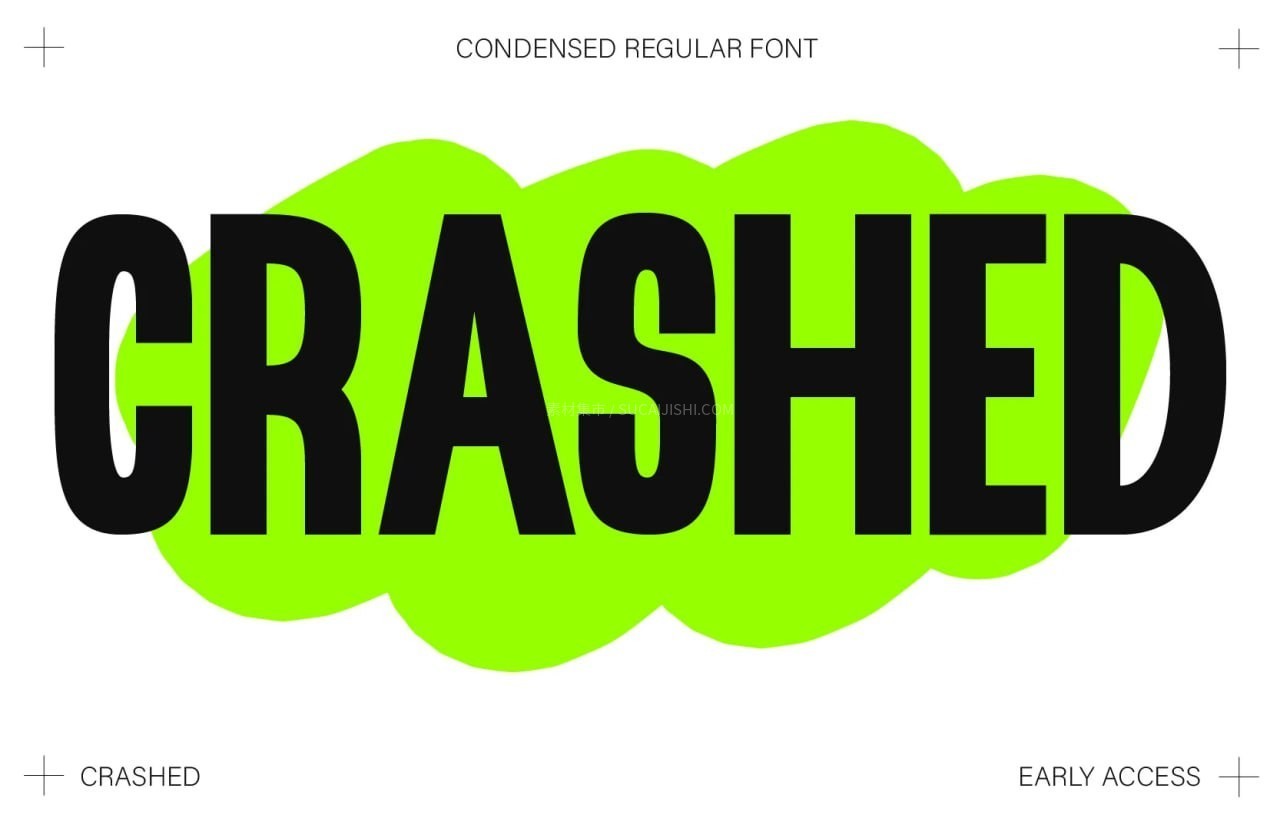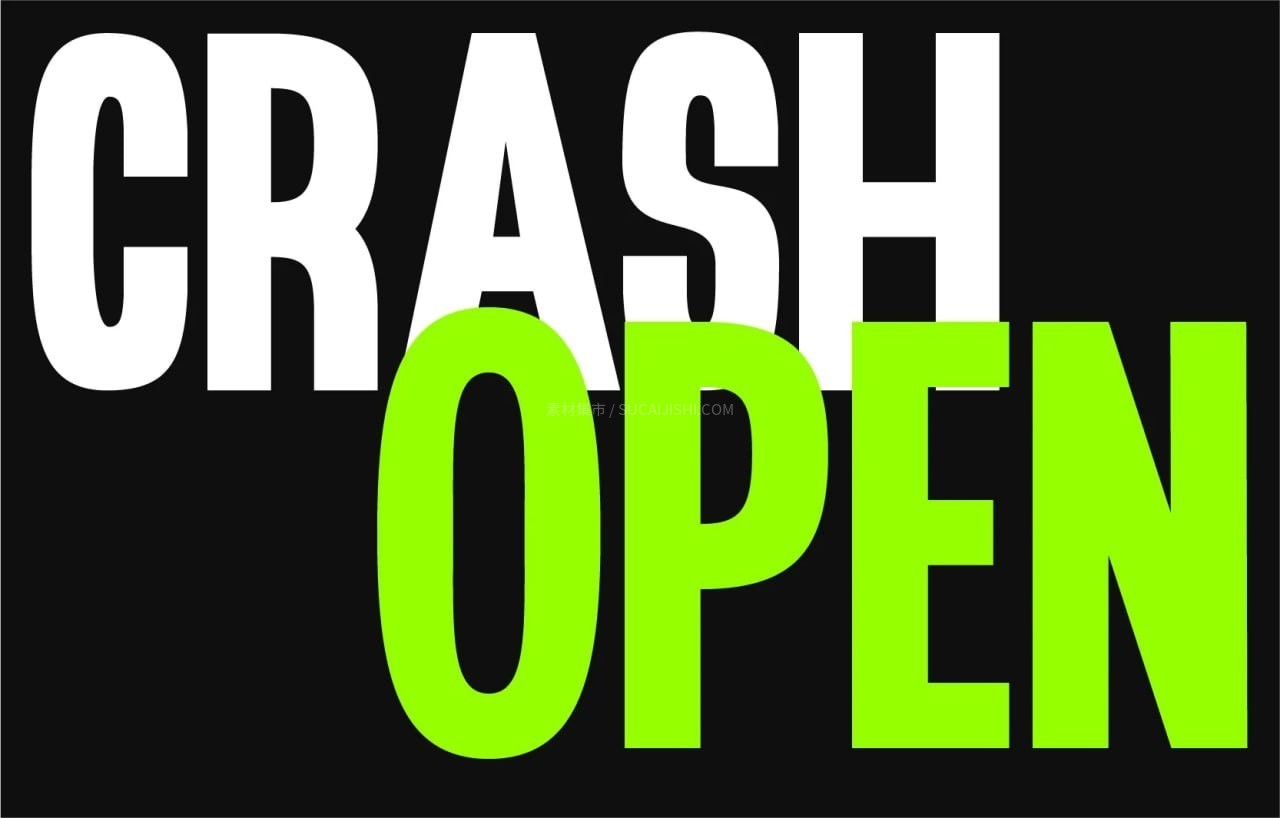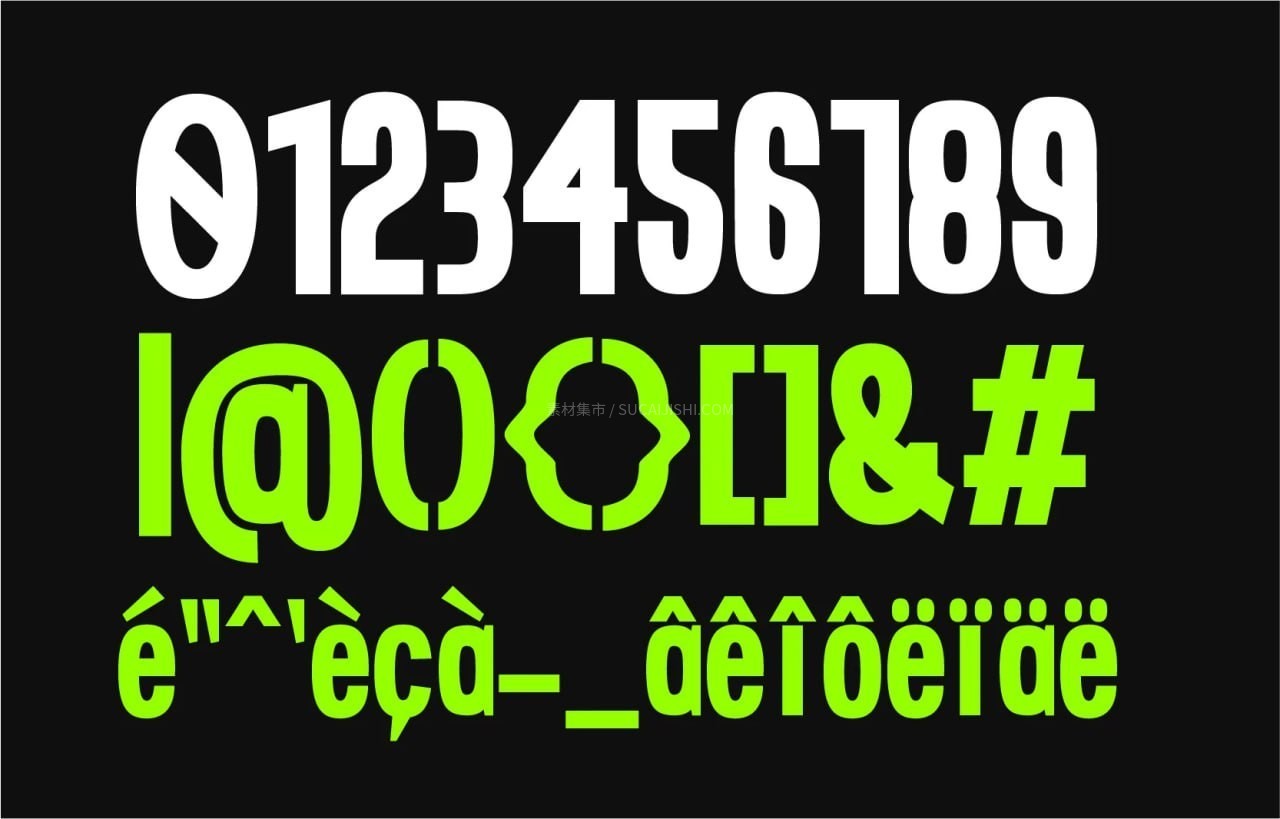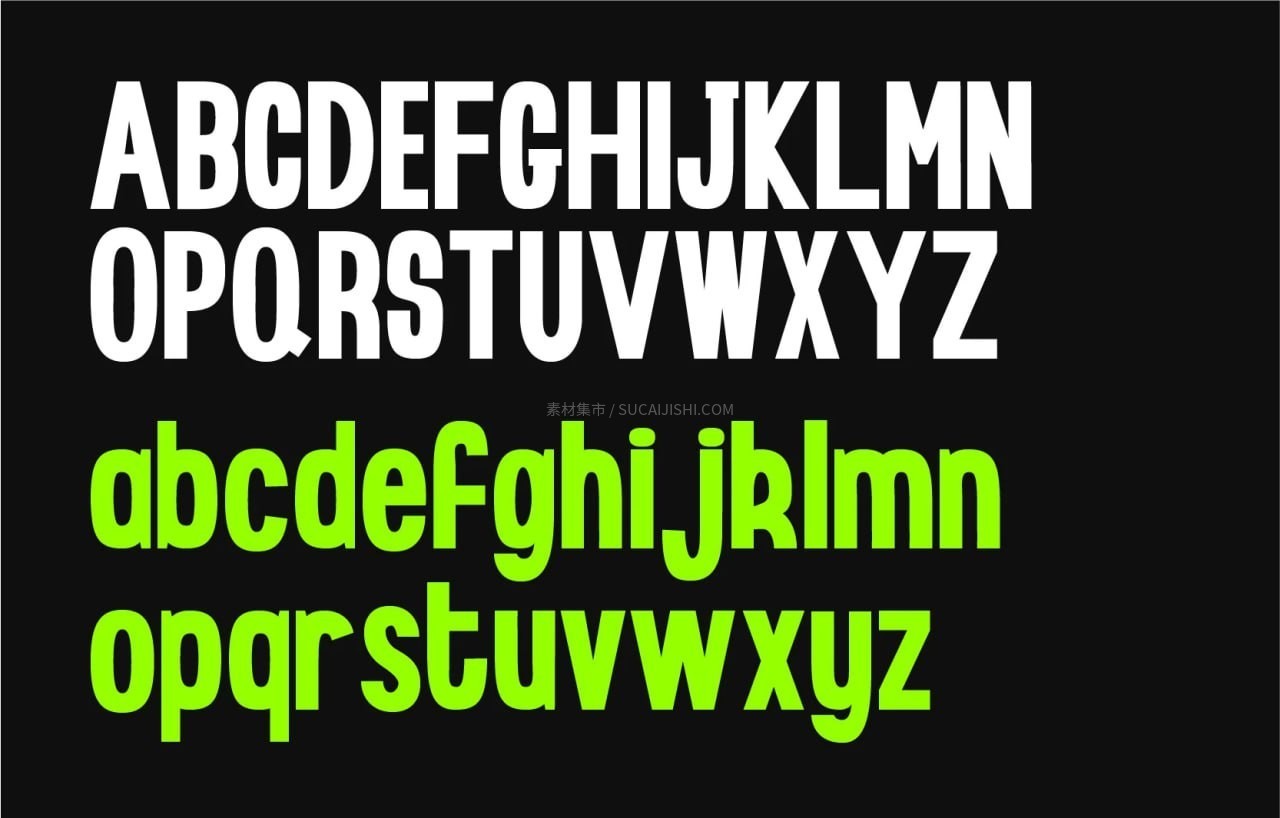
CRASH REGULAR 时尚标题英文字体,免费可商用
这是一款为现代审美而生的 CRASH REGULAR 英文字体。它具有极强的视觉张力和平面设计感,线条洗练且充满时尚感,能够轻松驾驭高级感十足的极简风格。该字体附带 免费商用协议,打破了版权限制,为设计师在追求先锋视觉与商业合规之间找到了完美平衡。